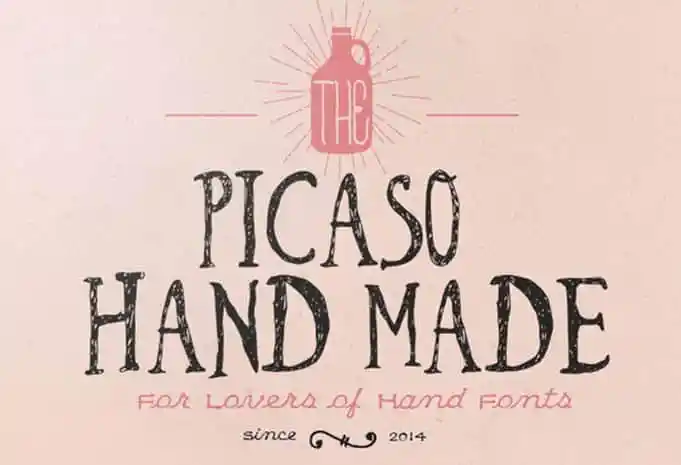
A Picaso Hand Made Font é uma graça entre as fuentes escritas a mão, desenhada pelo designer Hamilton e inspirada nos clássicos vintage do gênio Pablo Picasso. Esta fonte oferece um toque de charme e originalidade que se destaca em qualquer projeto gráfico, seja em elementos como selos ou sinalizações, embalagens, títulos, camisetas, aviso de propaganda, estandes de produto ou até mesmo a criação de peças para a internet. É uma fonte única criada pelo Bowery Studio Design que pode ser usada com liberdade em diversos formatos gráficos. Picaso Hand Made é o tipo de fonte desejável para quem busca trazer um toque especial e singular às suas criações, seja num design simples e funcional ou numa peça visualmente impactante.